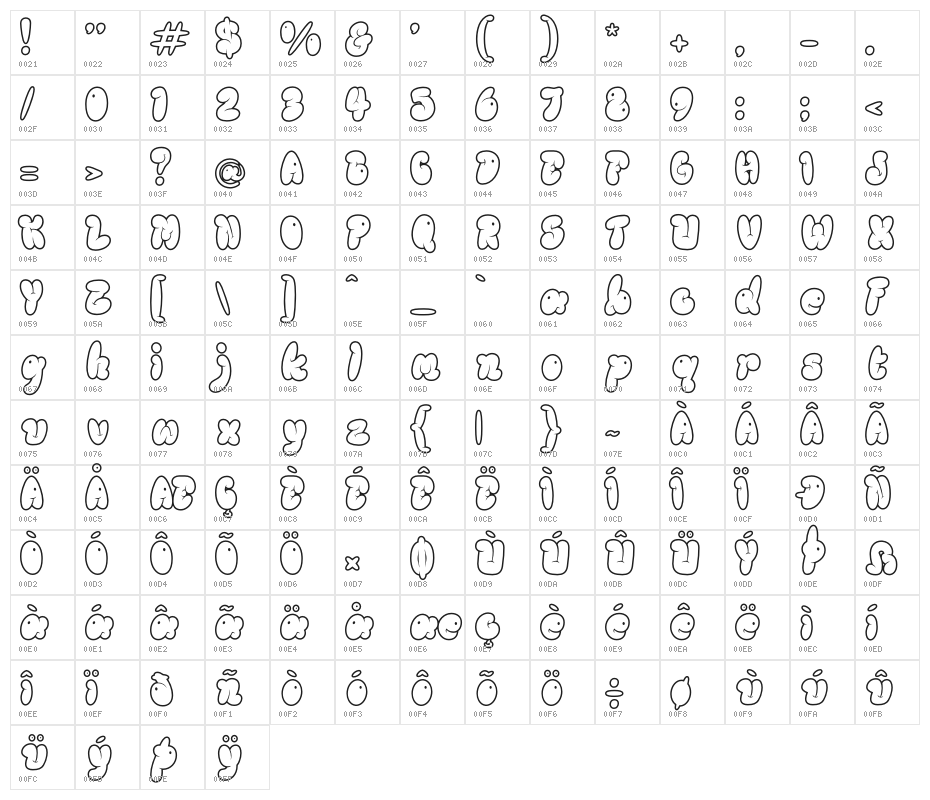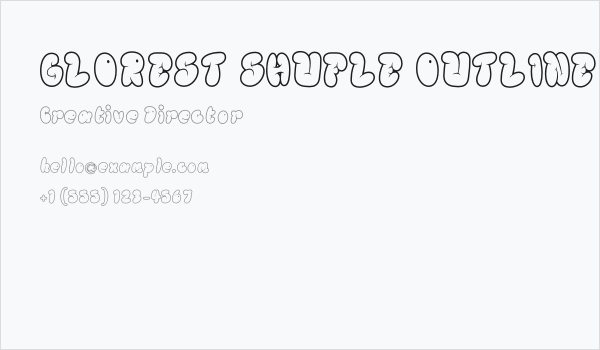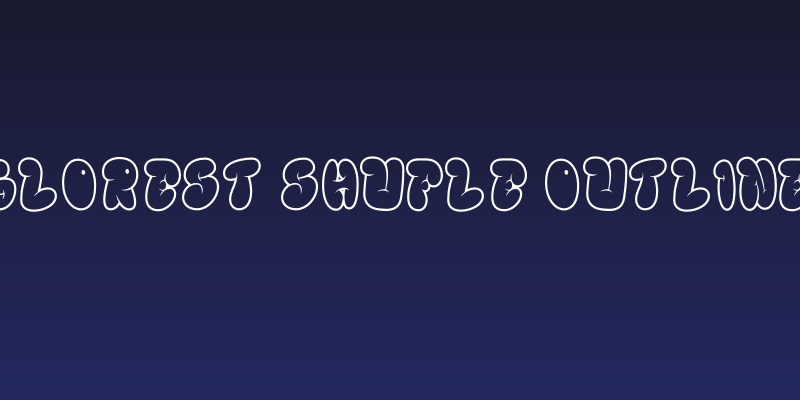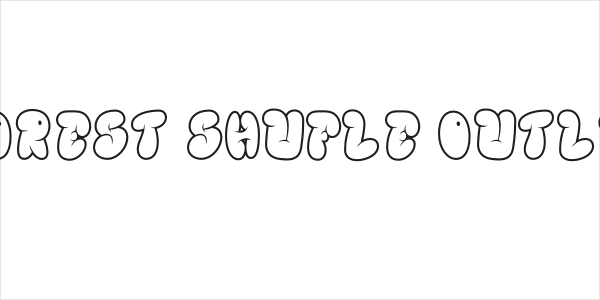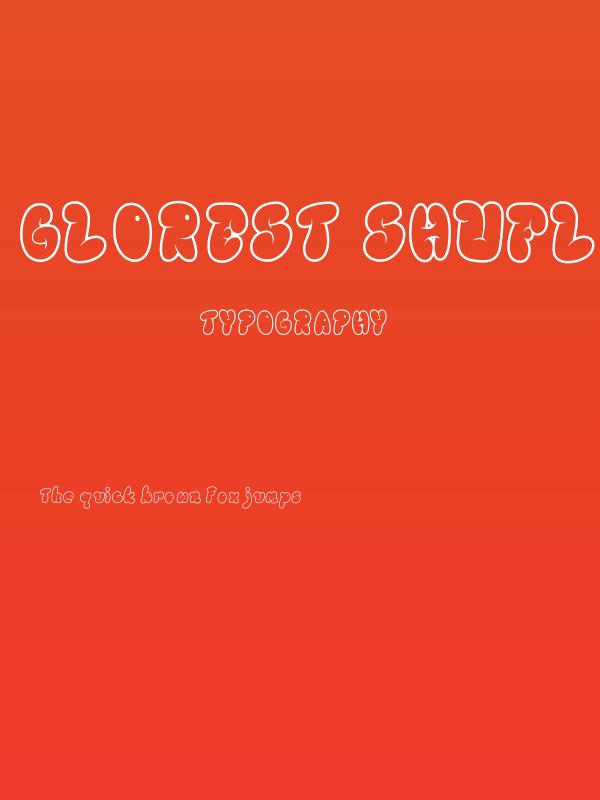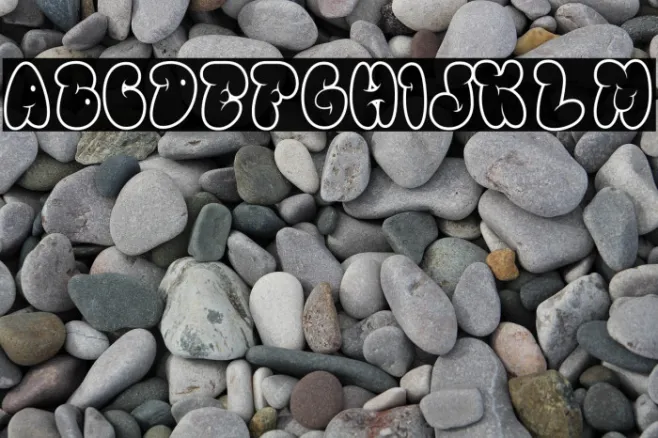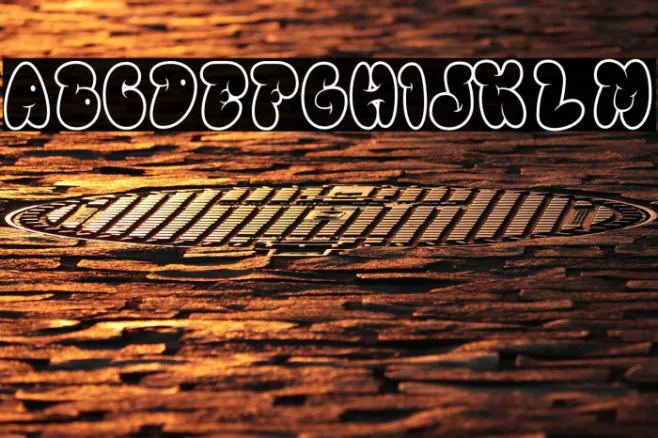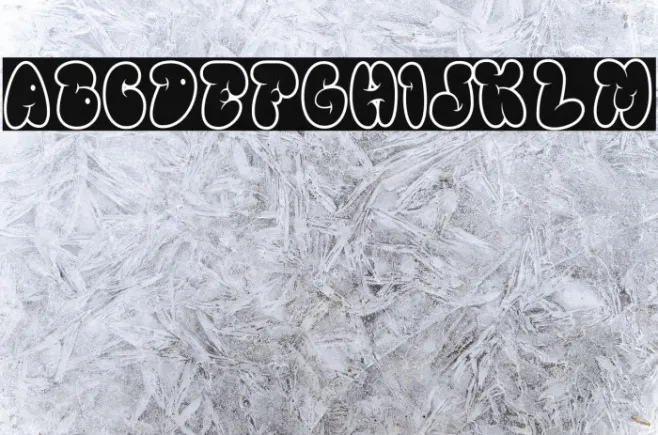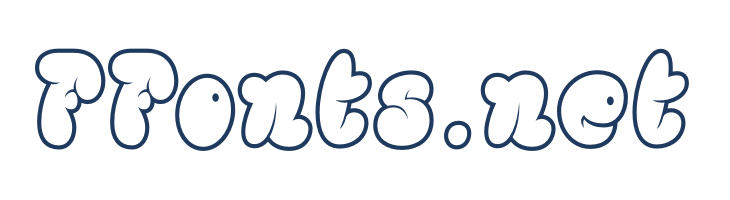
GLOREST SHUFLE OUTLINE Font
| Gesamtstil | Playful |
| Vorgeschlagene Projekte | Ideal for children's books, playful branding, party invitations, and cartoon-themed designs. |